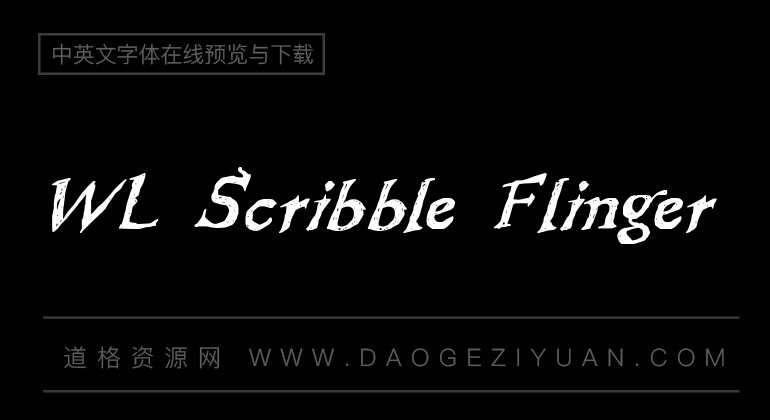
WL Scribble Flinger 是一种手写风格的字体,它的特点是仿照手写书写而设计,笔画干涩不平滑,具有一定的不规则性和随意性,给人一种自然、朴素的感觉。 该字体的字体家族包含粗体和斜体两种版本,可以用于设计海报、宣传资料、标志、包装等,并且适用于多种语言。它适合于需要有手写感觉或者需要营造亲近感的设计场景,比如教育、文化创意、儿童等。 WL Scribble Flinger 字体的设计者是来自美国纽约的设计师 Will L. Chang,他擅长于通过字体表达情感和创造力,他常常将自己的创作分享给社区,并受到了广泛的欢迎。内容介绍
WL Scribble Flinger是一款非常不错的手写艺术字体,具有很好的视觉感,适合于文化类的宣传设计、商业类品牌的广告和产品包装设计以及个性化文字排版等较多场景。